Trong số hàng ngàn lựa chọn font chữ trôi nổi trên các website hiện nay, rất khó để chúng ta có thể kiếm được bộ font chữ chuyên dụng cho ấn phẩm đồ họa của mình. Nếu bạn đang trải qua quá trình khó khăn tương tự, đừng lo, trong bài viết này G-Multimedia mang đến cho bạn 6 xu hướng font chữ đẹp trong năm 2022 sắp tới mà bạn cần biết để nâng cấp bản thiết kế của mình thêm phần đặc sắc nhé!
Typography là một trong số những yếu tố quan trọng nhất của thiết kế đồ họa. Một font chữ đẹp không đơn giản chỉ thể hiện nội dung tác phẩm, mà nó còn tác động tới cảm xúc của người xem. Một font chữ phù hợp sẽ thổi hồn vào bản thiết kế của bạn, tạo điểm nhấn mạnh mẽ và khiến người đọc đắm chìm hơn vào thông điệp mà bạn muốn truyền tải.
Tuy nhiên để tìm kiếm được các font chữ đẹp mắt và được ưa chuộng sẽ tốn của bạn không ít thời gian và công sức. Thay vào đó, G-multimedia đã tổng hợp giúp bạn 6 xu hướng font chữ xuất sắc cho năm 2022. Hãy cùng tìm hiểu nhé!
Font chữ viết tay (Handwriting font) là kiểu font chữ giả chữ người. Khác với các loại font chữ đẹp không chân và có chân, Font chữ Handwriting mang đến nét lộn xộn, rối ren nhưng vẫn mềm mại cho thiết kế của bạn. Sự xuất hiện của Handwriting gợi cảm giác bàn tay con người đã tạo nên, giống như một chữ kí cá nhân. Từ đó xây dựng được mối quan hệ gần gũi giữa người truyền tải và người xem. Tuy nhiên một lưu ý nhỏ là vì giả chữ người nên đôi khi font chữ viết tay có thể hơi khó đọc, hãy chọn font thật kĩ trước khi sử dụng bạn nhé!
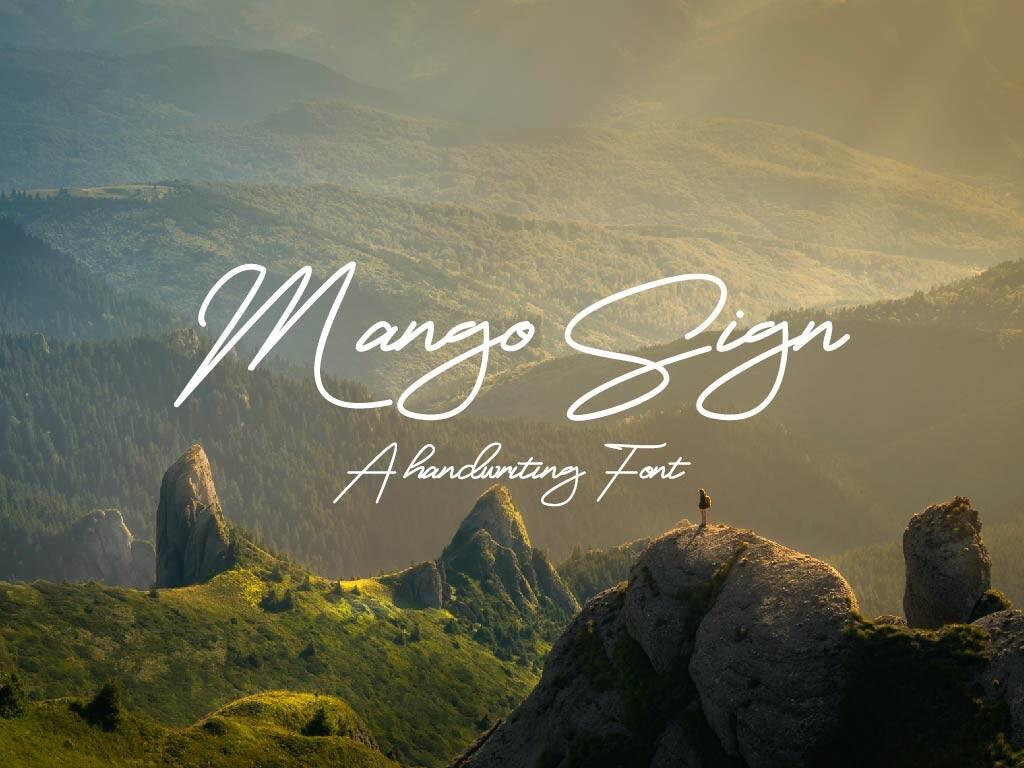
Font chữ có chân với độ tương phản cao (High-contrast serif font) được lấy cảm hứng từ nét chữ viết của Nhật Bản. Với nét cân bằng giữa truyền thống và hiện đại, đây là một font chữ đẹp đem đến sự thanh lịch và trang trọng cho thiết kế của bạn. Điểm nổi bật của font chữ này chính là sự tương phản giữa độ dày của các nét tạo nên tính khác biệt không thể nhầm lẫn.
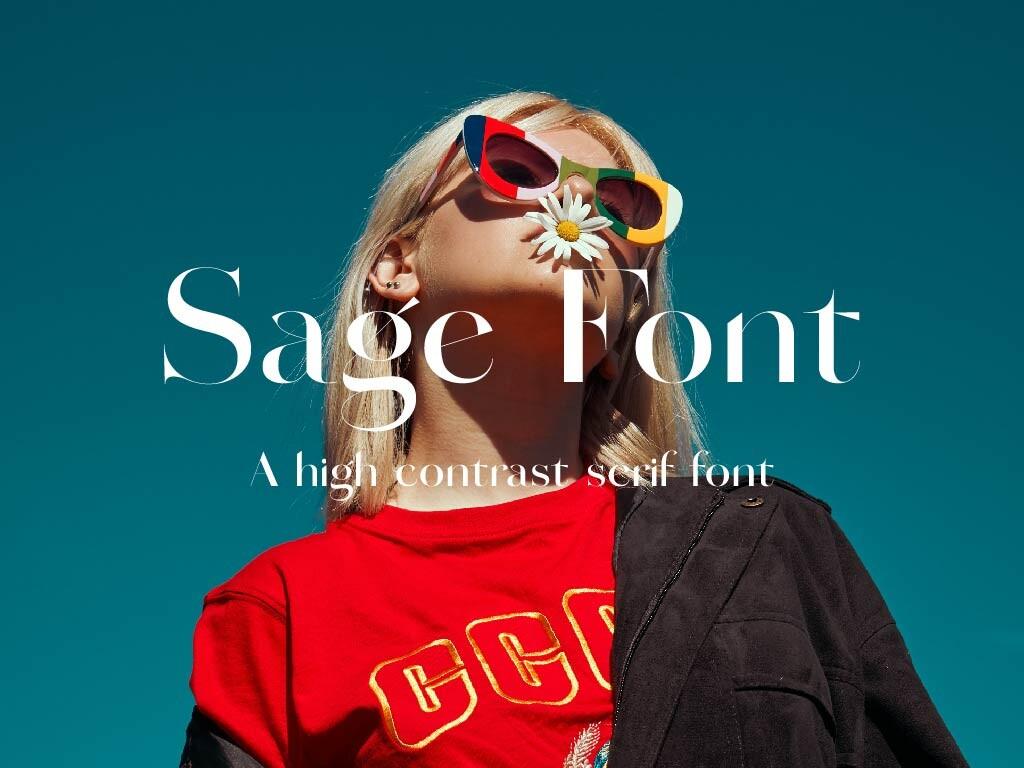
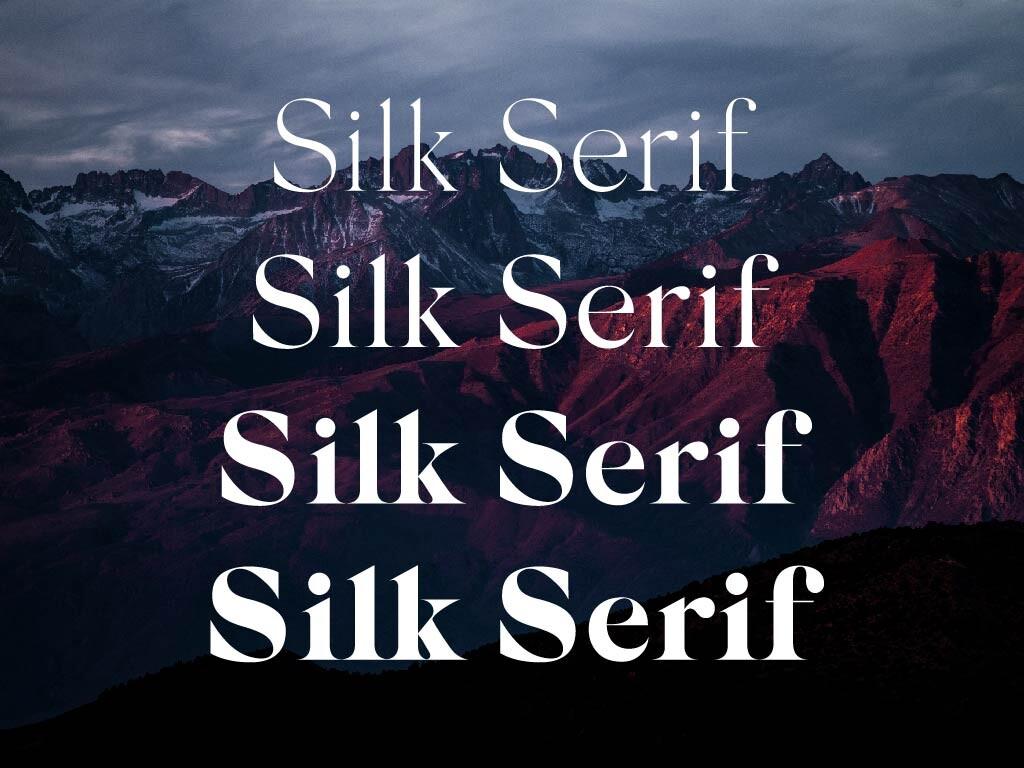
Display Script là font chữ được sử dụng rộng rãi trên các bảng quảng cáo, bìa tạp chí, đặc biệt là bìa tạp chí thời trang. Tính thẩm mĩ của font chữ là sự kết hợp giữa các thể loại như: nét chữ thủ công và thư pháp. Display Script rất đa dạng về hình dáng, kích cỡ, độ dày...Tuy nhiên, G-Multimedia gợi ý cho bạn những font chữ đẹp cụ thể như: Gallery modern, Yipe Font, Bon Foyage, saint monica font. Các font chữ này có đặc điểm chung là nét chữ khá thanh mảnh, có nét cong vô cùng đặc trưng, thể hiện rõ sự sang trọng và hiện đại.
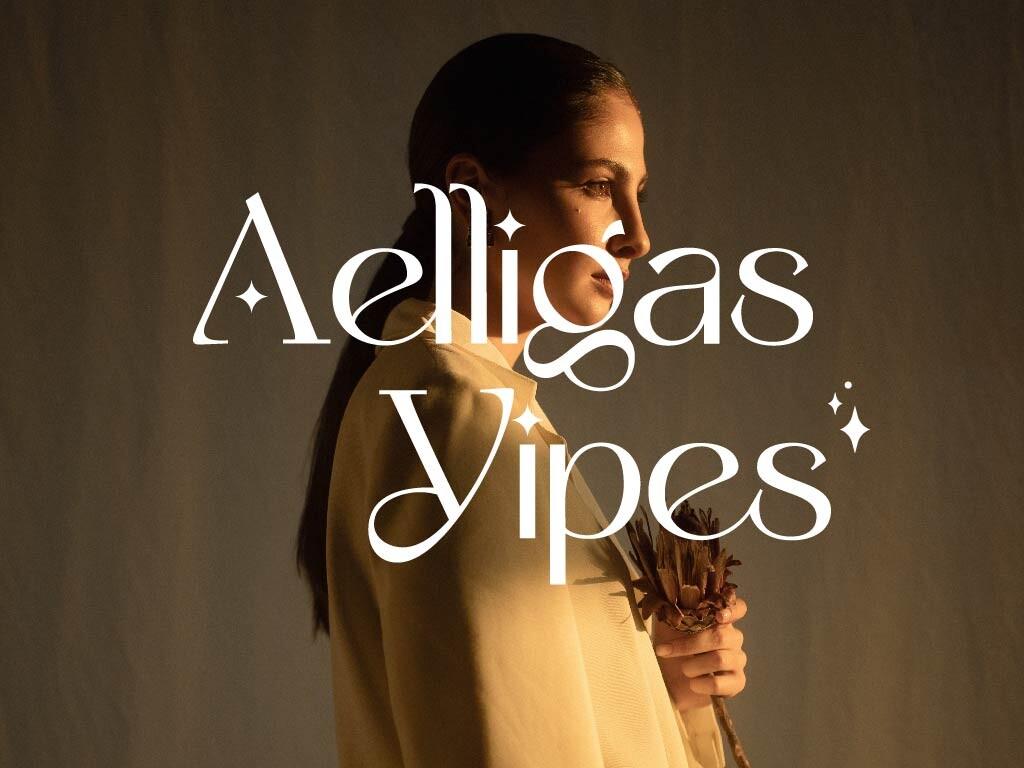
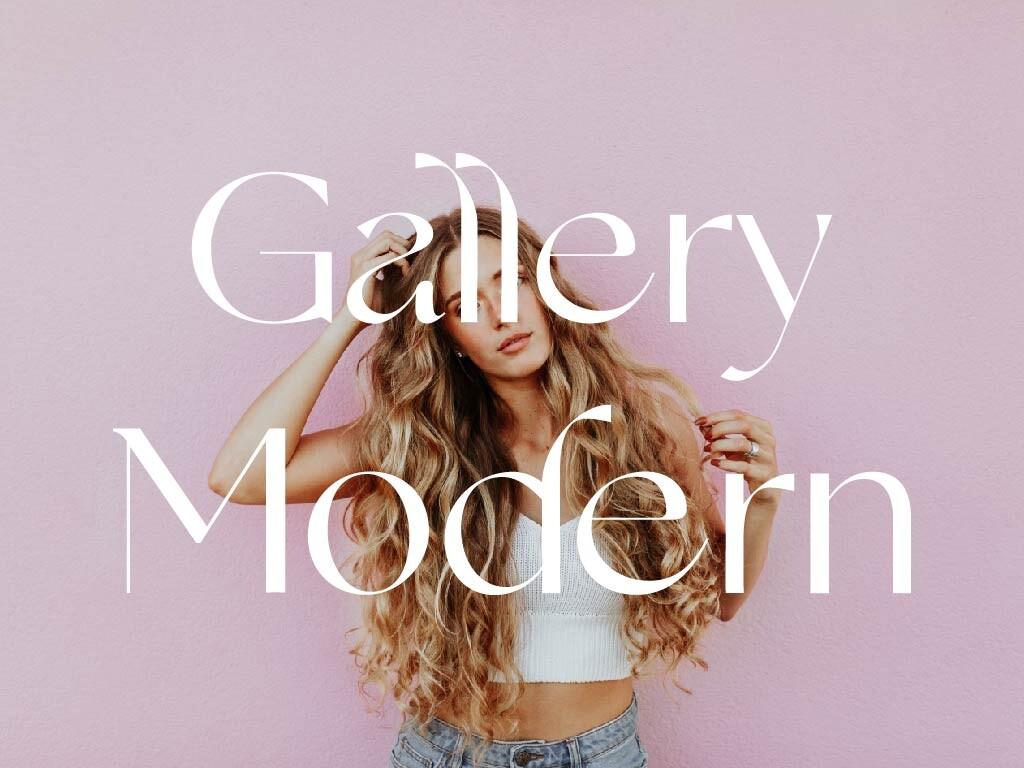
Font chữ tròn (Rounded font) thường hiện diện trong các bản thiết kế dành cho trẻ em bởi các cạnh góc tròn thân thiện của chúng. Vậy nhưng sự phá cách trong nét cạnh, font chữ tròn đã dần chiếm được cảm tình của cả đối tượng khán giả lớn tuổi. Nét tròn của font chữ mang tới sự tối giản cần thiết, không màu mè và thay vào đó là nét tinh tế hoàn hảo.
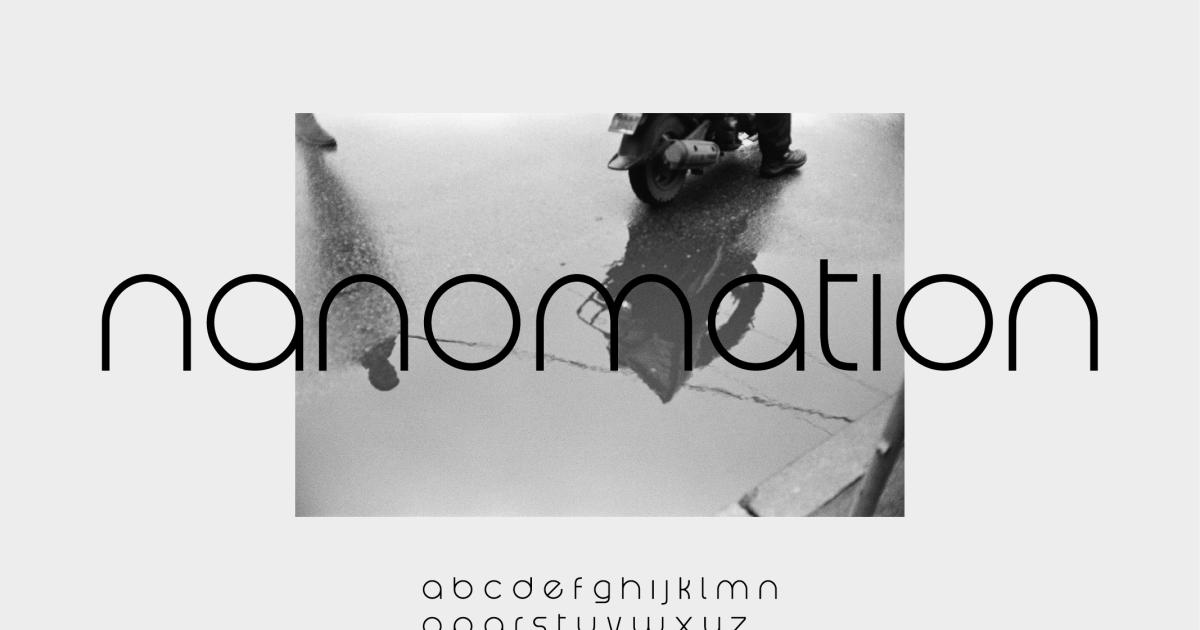
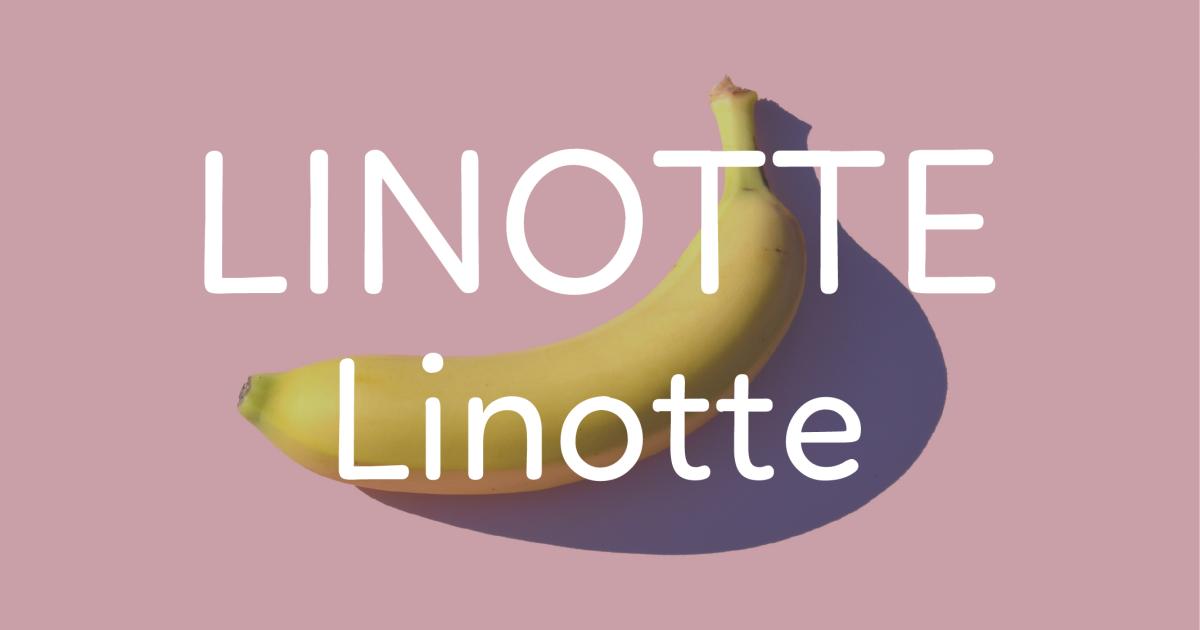
Font chữ không chân (San serif) chính là biểu tượng cho câu nói "Less is more". Đây là font chữ rất phổ biến và chưa bao giờ hết "hot". Với các đặc điểm rất dễ dùng như gọn gàng, hiện đại, nét chữ đều nhau, San serif là font chữ đẹp mà bất cứ designer nào cũng cần phải biết tới.
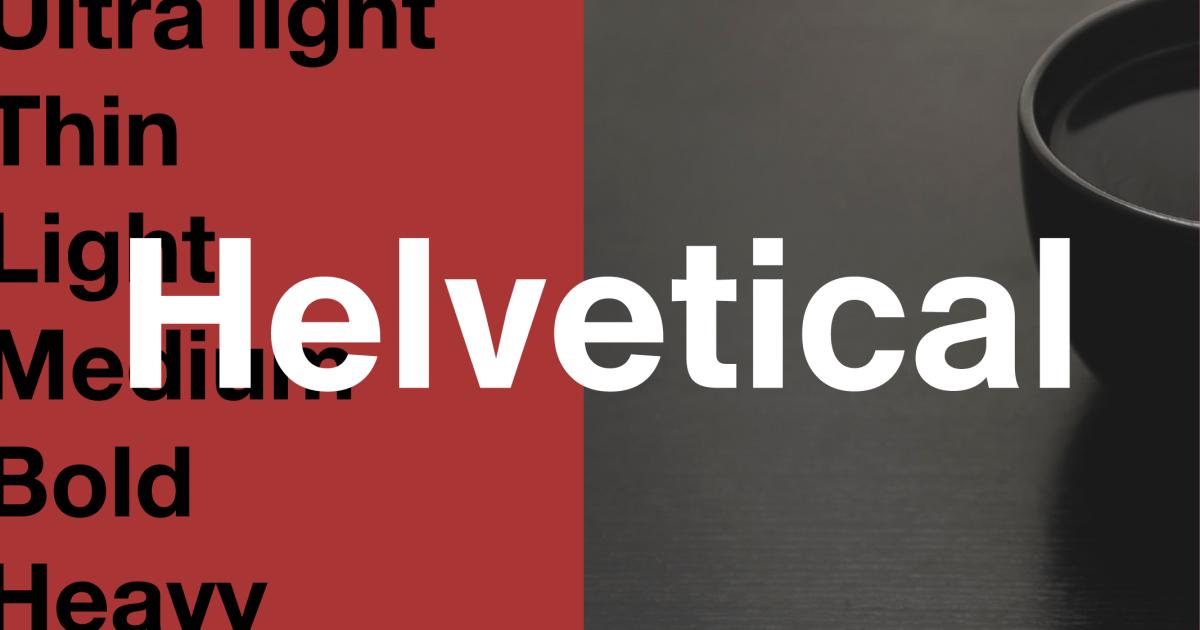
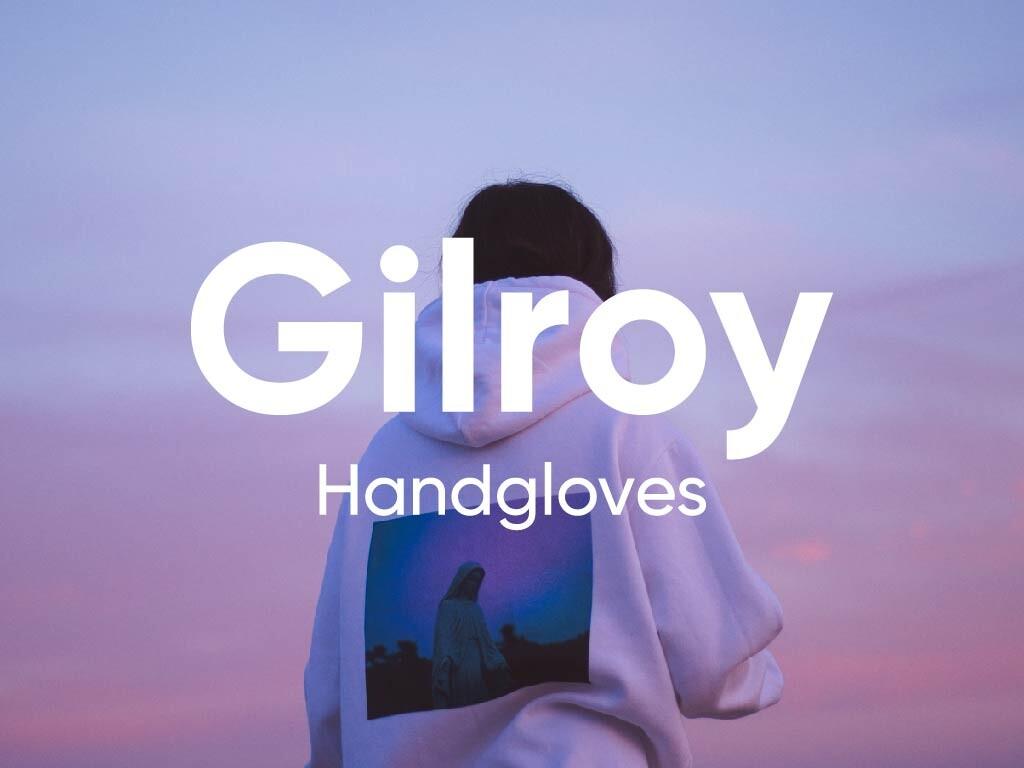
Font chữ Retro mang tới nét cổ điển vượt thời gian cho các tác phẩm của bạn. Nét chữ cong, uốn lượn của font chữ đưa người đọc quay trở về thời kì những năm 1970, 1980. Đặc biệt thời gian gần đây font chữ đẹp đẽ này đang dần được sử dụng với độ dày to đem đến hơi hướng phóng khoáng, bụi bặm và phong trần. Ngoài ra font Retro còn truyển tải cảm xúc tích cực và vui vẻ. Nếu mục đích của bạn là mang đến nụ cười dành cho khán giả, thì font Retro dạng chữ to (Chubby Retro font) là lựa chọn vô cùng hợp lý.